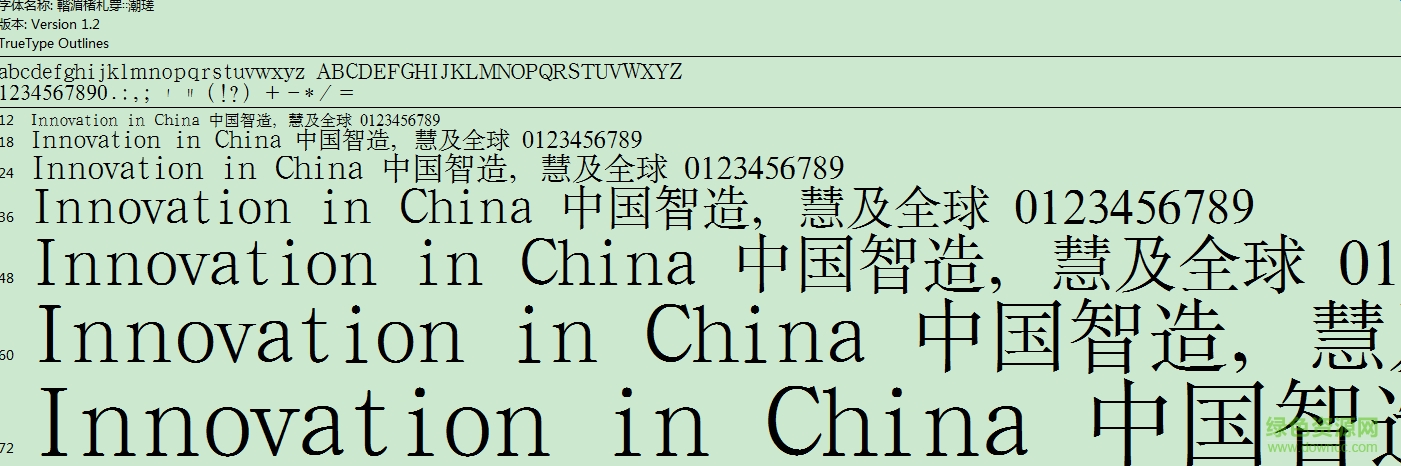
漢鼎簡(jiǎn)書(shū)宋二字體是一款宋體字體,適用于廣告藝術(shù)射擊等方面,美工的同學(xué)們不要錯(cuò)過(guò)喲,使用字體能讓你的設(shè)計(jì)風(fēng)格變化多樣,充滿剛毅性。喜歡就快來(lái)綠色資源網(wǎng)免費(fèi)下載吧!
目前它廣泛的運(yùn)用在排版印刷等行業(yè)。在保留了宋體字體的字形的同時(shí)加入了漢鼎字體的特色風(fēng)格,讓人有耳目一新的感覺(jué),超級(jí)有個(gè)性!